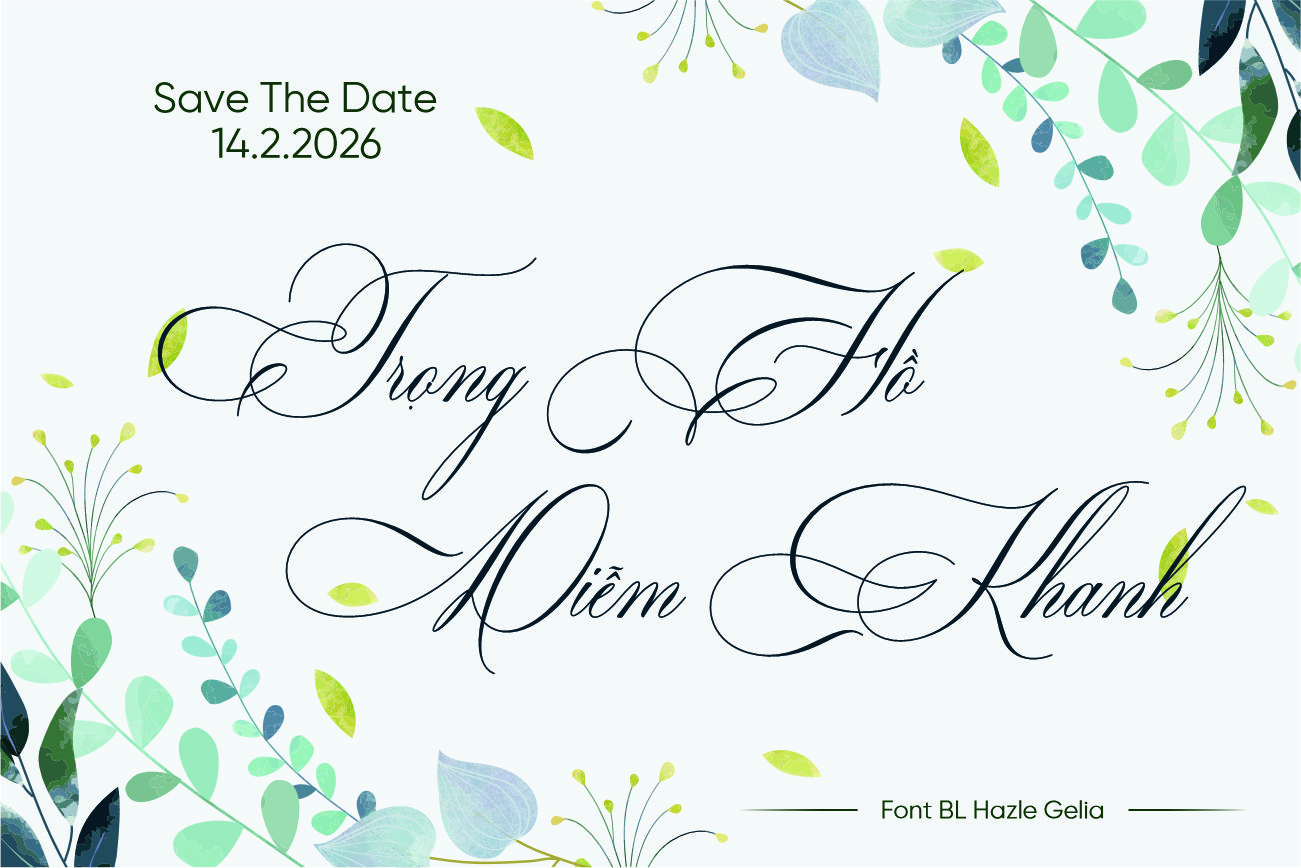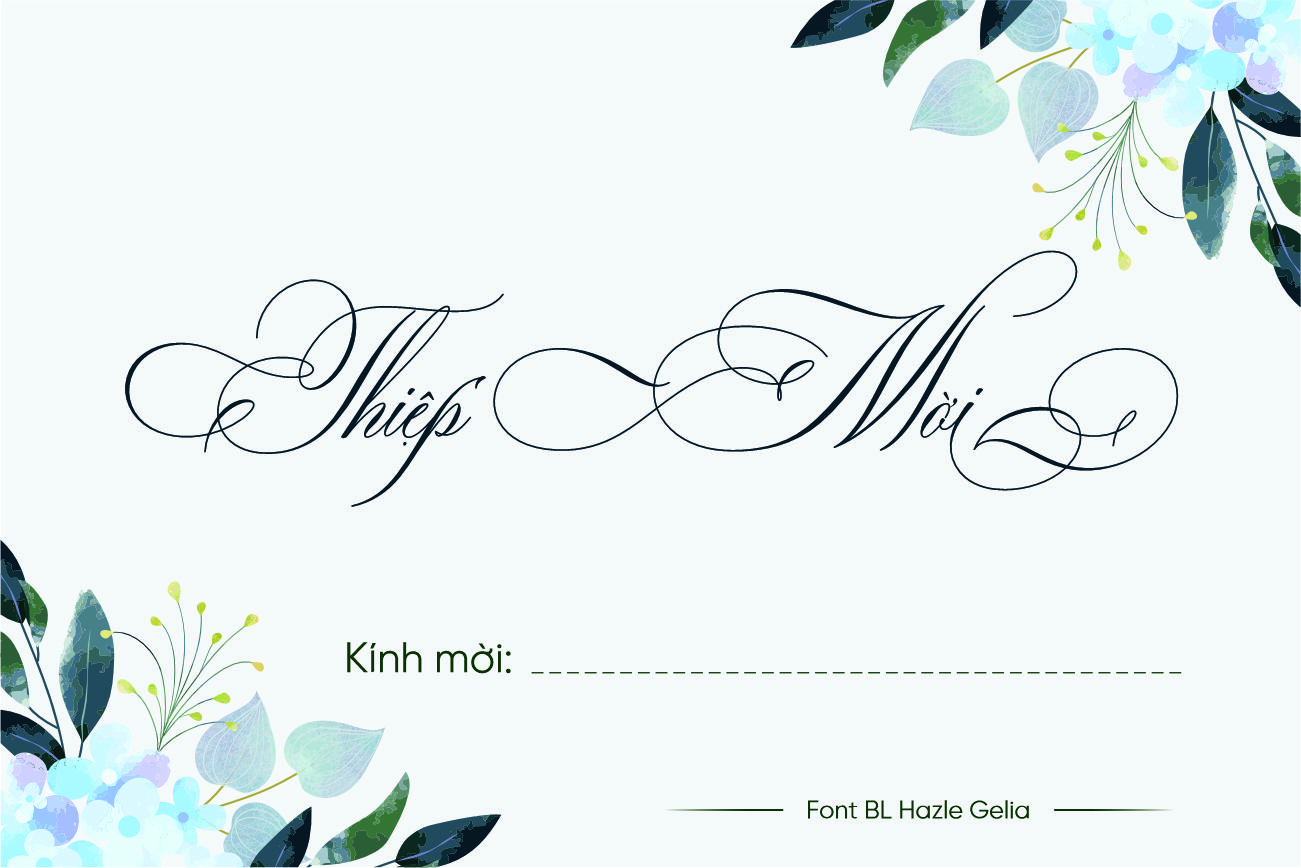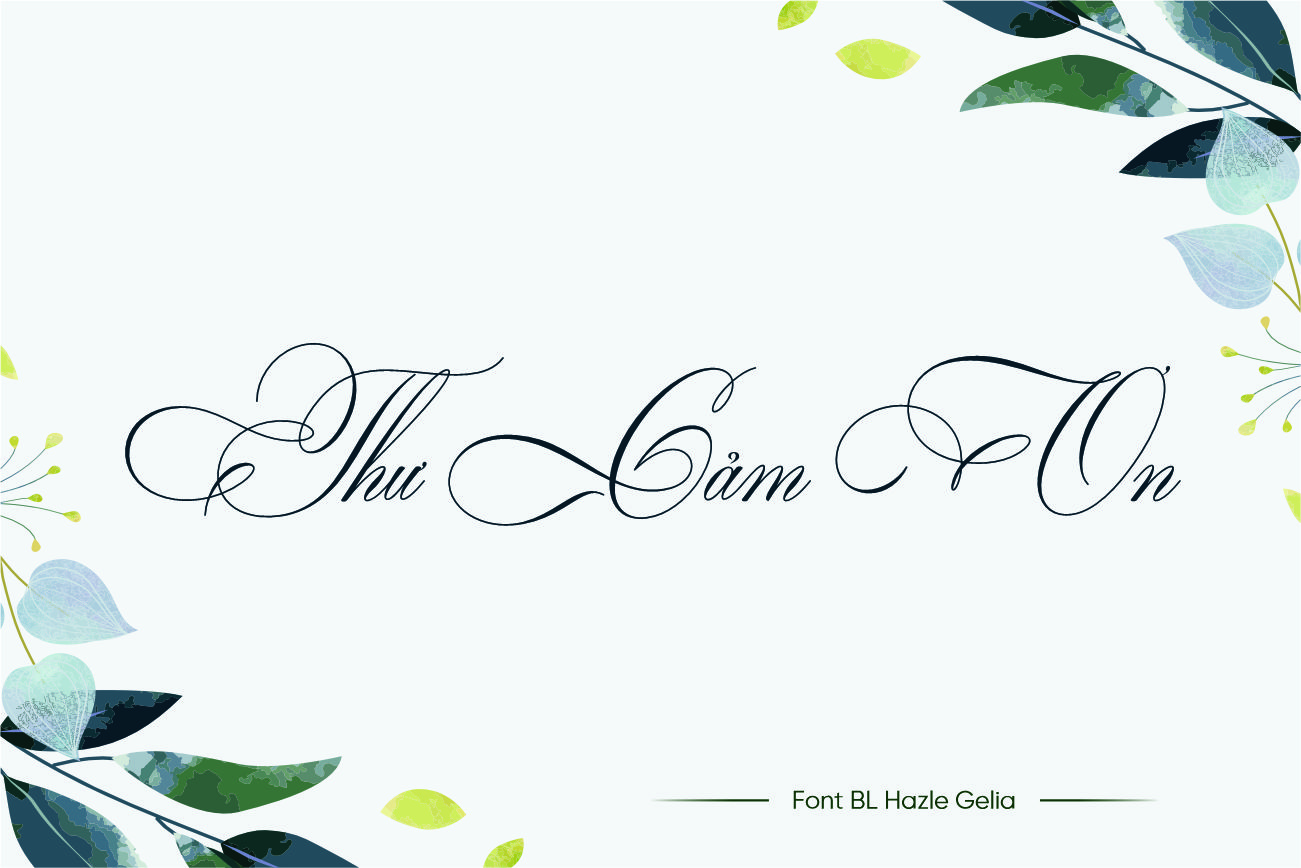
Font Chữ Script Viết Tay Lãng Mạn - BL Hazle Gelia Việt Hóa
Trong thiết kế thiệp cưới, việc chọn font chữ đẹp cho thiệp cưới là yếu tố quyết định để tạo nên ấn tượng ban đầu cho khách mời. Một kiểu chữ tinh tế không chỉ làm nổi bật nội dung mà còn truyền tải được phong cách và cá tính riêng của cô dâu chú rể. Bởi vậy, xu hướng hiện nay là ưu tiên những font chữ viết tay lãng mạn như font BL Hazle Gelia với đường nét mềm mại, uyển chuyển và giàu cảm xúc.
Điểm mạnh của font chữ viết tay là mang lại sự gần gũi, tự nhiên và cá nhân hóa. Khi xuất hiện trên thiệp cưới, mỗi con chữ trở nên sống động, giúp lời mời trở nên chân thành và đầy cảm xúc. Những font có chi tiết swash, ligature hoặc flourishes càng làm tăng thêm vẻ nghệ thuật, biến tấm thiệp trở thành một tác phẩm tinh xảo. Đây cũng chính là lý do font chữ thiệp mời sang trọng như font BL Hazle Gelia ngày càng được sử dụng nhiều trong các sự kiện cưới hỏi cao cấp.
Ngoài ra, thị trường hiện nay có nhiều dòng font chữ script cao cấp như font BL Hazle Gelia đã được Việt hóa hoàn chỉnh, hỗ trợ đầy đủ dấu tiếng Việt. Những font này không chỉ giữ nguyên tinh thần nghệ thuật của bản gốc mà còn dễ dàng áp dụng trong thiết kế thiệp cưới, thiệp cảm ơn, poster hay logo. Với hệ thống ký tự đa dạng, chúng mang lại cho designer nhiều lựa chọn sáng tạo để phù hợp với từng phong cách, từ cổ điển đến hiện đại.
Tóm lại, nếu bạn muốn tạo dấu ấn cho ngày trọng đại, hãy lựa chọn những font chữ đẹp cho thiệp cưới mang phong cách viết tay lãng mạn và sang trọng như font BL Hazle Gelia. Một kiểu chữ tinh tế, được thiết kế chuyên nghiệp sẽ nâng tầm thẩm mỹ cho thiệp cưới, đồng thời khắc ghi cảm xúc trong lòng người nhận.